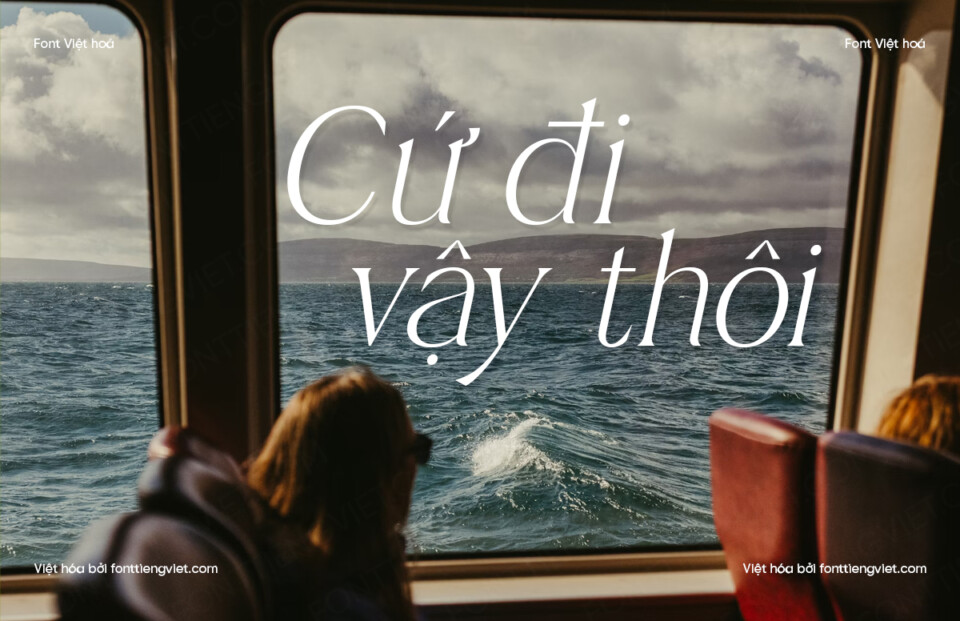
Font Việt hóa 1FTV VIP Brikey Moura Italic
Giới thiệu về bộ Font Việt hóa 1FTV VIP Brikey Moura Italic
Trong thế giới thiết kế đồ họa hiện đại, việc lựa chọn một bộ Font Miễn Phí nhưng vẫn đảm bảo được tính thẩm mỹ và chuyên nghiệp là điều vô cùng quan trọng. Font Việt hóa 1FTV VIP Brikey Moura Italic xuất hiện như một làn gió mới, mang lại sự tinh tế và đẳng cấp cho mọi dự án sáng tạo. Đây là phiên bản nghiêng đặc biệt, được tinh chỉnh kỹ lưỡng về dấu tiếng Việt để người dùng tại Việt Nam có thể sử dụng mượt mà trong các phần mềm thiết kế như Photoshop, Illustrator hay Canva. Với các đường nét thanh mảnh nhưng chắc chắn, bộ font này không chỉ dừng lại ở việc hiển thị văn bản mà còn truyền tải được cảm xúc và sự sang trọng của một tác phẩm nghệ thuật thực thụ.
Đặc điểm nổi bật của Font Việt hóa 1FTV VIP Brikey Moura Italic
Điều làm nên sự khác biệt của Font Việt hóa 1FTV VIP Brikey Moura Italic chính là sự kết hợp hoàn hảo giữa phong cách cổ điển và hơi thở đương đại. Kiểu chữ nghiêng (Italic) của bộ font này không quá lạm dụng độ dốc, tạo cảm giác chuyển động nhẹ nhàng và thanh thoát. Các ký tự được thiết kế với khoảng cách tối ưu, giúp văn bản dễ đọc ngay cả ở kích thước nhỏ. Đặc biệt, quá trình Việt hóa đã được thực hiện tỉ mỉ, đảm bảo các dấu thanh như huyền, sắc, hỏi, ngã, nặng được đặt ở vị trí cân đối, không làm biến dạng cấu trúc gốc của chữ cái. Đây là yếu tố then chốt giúp các designer tiết kiệm thời gian chỉnh sửa thủ công khi thiết kế các ấn phẩm tiếng Việt phức tạp.
Ứng dụng thực tế của Font Việt hóa 1FTV VIP Brikey Moura Italic
Nhờ vẻ ngoài lịch lãm, Font Việt hóa 1FTV VIP Brikey Moura Italic thường xuyên được ưu tiên sử dụng trong các lĩnh vực yêu cầu tính thẩm mỹ cao. Bạn có thể dễ dàng bắt gặp bộ font này trên các bìa tạp chí thời trang, thiệp mời đám cưới sang trọng hoặc các banner quảng cáo mỹ phẩm cao cấp. Đối với các bạn học sinh và sinh viên, việc sử dụng font chữ này trong các bài thuyết trình hay thiết kế kỷ yếu sẽ giúp nội dung trở nên nổi bật và chuyên nghiệp hơn hẳn các phông chữ hệ thống thông thường. Ngoài ra, trong thiết kế nhận diện thương hiệu, kiểu chữ này rất phù hợp để làm slogan hoặc các đoạn trích dẫn ngắn, giúp thu hút thị giác và tạo điểm nhấn mạnh mẽ cho người xem ngay từ cái nhìn đầu tiên.
Cách tối ưu hóa Font Việt hóa 1FTV VIP Brikey Moura Italic trong trình bày
Để phát huy tối đa vẻ đẹp của Font Việt hóa 1FTV VIP Brikey Moura Italic, người thiết kế nên kết hợp nó với các font chữ không chân (Sans-serif) tối giản cho phần nội dung chính. Sự tương phản giữa nét nghiêng điệu đà của Brikey Moura và nét thẳng hiện đại sẽ tạo nên một bố cục cân bằng, hài hòa. Bên cạnh đó, việc sử dụng các tông màu trung tính như vàng đồng, đen tuyền hoặc trắng kem sẽ giúp bộ font này toát lên vẻ thượng lưu. Đừng quên chú ý đến khoảng cách dòng (leading) để đảm bảo các nét nghiêng không bị chồng lấn vào nhau, giữ cho bản thiết kế luôn sạch sẽ và tinh tế trong mắt người dùng.